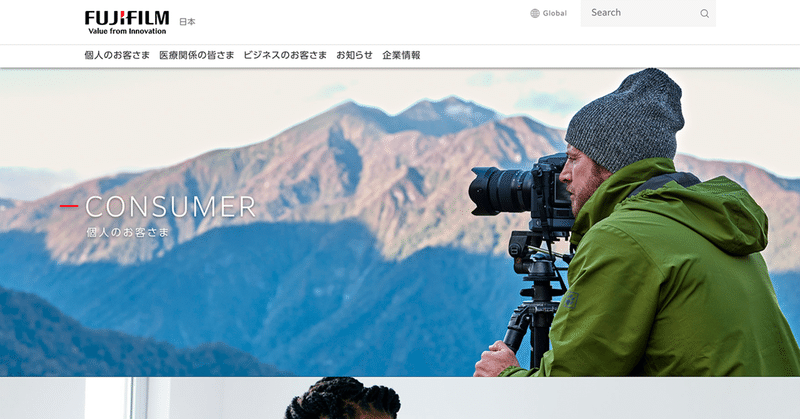
【インタビュー】わたしの“推し”フォント 第8回 桑原 翔(1PAC. INC.)「視覚効果は削ぎ落とせても文字はなくせない。文字の持つ表情がエンドユーザーの印象を決める」
いま、私たちは情報の多くを文字から受け取っています。メディアの中心が印刷物からスクリーンに変わってもなお、文字がコミュニケーションのひとつの要であることは変わりません。
「My MORISAWA PASSPORT わたしの“推し”フォント」では、さまざまなジャンルのデザイン、その第一線で活躍するデザイナーに、文字・フォントをデザインワークのなかでどのように位置づけ、どのような意図・考えで書体を選択しているのかをインタビュー。あわせて、「MORISAWA PASSPORT」“推し”フォントを紹介いただきます。
第8回は、Webサイトを中心にデジタルサイネージ、アプリケーションなどのアートディレクション、フロントエンドのコーディングを手がけるワンパク(1PAC. INC.)の桑原さんにお話を伺いました。
1.デザインがシンプルになることで書体がより重要に
もともとは映像やデジタルアートに興味があったという桑原さん。フォントへの関心が強くなったきっかけは、Webデザインの変遷によるものが大きかったそうです。
「私が最初にWeb表現に興味を持ったのは大学生の頃で、Flash の全盛期でした。Webでこんなことができるのかと思ったのが、この仕事に就くきっかけになっています。
今のWebはパーティクル等の表現やデコレーションが削ぎ落とされ、デザインもシンプルになる傾向ですが、視覚要素が減っても文字は絶対なくなりません。むしろ装飾が少なくなることで、書体が持っている表情がエンドユーザーの印象を決める重要な役割を持つようになったと思います」
Web制作においては、技術の進歩がデザインに変化をもたらします。桑原さんにとって特に大きかったのは、Webフォントの存在でした。
「Webフォントが出始めた頃は、表示速度の問題で部分的にしか使用することができませんでしたが、いまはその心配もありません。すべての文字をWebフォントにすることも可能で、書体を自由に考えることができるようになりました。3G時代と4G時代で提案できるデザインが変わったことを実感しています。
また液晶画面の高精細化が進み、細い文字でもパキッと見えるようになってきました。以前なら見出しには太い文字、というのがセオリーでしたが細い文字を大きく使う、などの表現も今ではよく使われる手法になっています」
また文字情報が多いときには、読みやすさを一番に意識するようにしているそうです。
「装飾性の高いフォントを本文にしてしまうと、読むときにパワーが必要になります。たくさんの文字を読みやすくするにはフォント選びはもちろんですが、文字の配置を数値的に管理して最適な行間や段落間隔を設計するようにしています」
2.作るもののキャラクターに合わせたフォント選び
文字情報の多いWebサイトの場合、読みやすいフォントを選ぶことが最も重要です。スマートフォンや高精細なディスプレイなど、さまざまなデバイスでの見え方も考慮して選ぶ必要があります。
「フォントを選ぶときにはまず、MORISAWA PASSPORTの書体を見ていきます。好きなフォントはもちろんありますが、作ろうとしているデザインのキャラクターに合うかどうかが一番重要です。
コーポレートサイトならブランディングを達成する必要がありますし、法人格としてのキャラクターや世の中に対してのスタンス、世間から認知させたいイメージと合っているかどうかですね」
フォントは「声」のようなものだと語る桑原さん。どの声を選ぶかは、制作チームとクライアントを交えて検討を重ね、決定するのだそう。
「案件がキックオフしてから1~2ヶ月かけてディスカッションします。誰のためのものなのか?どんなブランドイメージなのか?柔らかく見せたいのか、クールな感じを出したいのか?などワークショップを重ねながら、制作とクライアントとが同じ目線に立てるように話し合っていきます。
フォントは書体見本を見て決めるのではなく、実際にメインのコピーをいろんなフォントで試してみてどの声色が一番伝わるかを確認しながら選びます。特に書体レギュレーションが決まっていないサイトリニューアルの仕事の場合、検討するフォントの数もかなり多くなりますね」
MORISAWA PASSPORTを選ぶ理由は、日本語フォントの数が多いこととWebフォントとしてTypeSquareで使えることが挙げられるそうです。
「MORISAWA PASSPORTは、日本語表現をするなら必ず通る道のようなもので、日本語をここまで長く多く使っているメーカーは他にありませんよね。ワンパクではデザインの担当だけでなく、実装担当やディレクターもMORISAWA PASSPORTを入れています。
書体数がものすごく多いし、常に新しい書体が増えていくところがいいです。インストールも簡単なので、新しいフォントもタイムリーにどんどん使っていこうと思えます」
3.桑原さんのデザイン&書体実例
桑原さんの手がける仕事の中でも、特に規模が大きく時間をかけて作られているのがコーポレートサイトです。富士フイルムのコーポレートサイトのトップページはBtoB、BtoCを統合したハブのようなものになっているのだそう。
「富士フイルム様の場合、もともとコーポレート書体として使用されていた新ゴの印象値を維持しつつ、今の時代に合わせてUD新ゴの細めのウエイトをセレクトしました。欧文部分は多言語に対応できるClarimo UDです。文字が多いページでも読み込みが速く、アクセスした瞬間にWebフォントに切り替わる速度感がアピールポイントです」
「スマートフォンサイトではUD新ゴ コンデンス90を使っています。PCサイトの新ゴのイメージと統一させつつ、スマートフォンの狭い横幅でも文字数を入れることができるよう考えました」
デザイン部分を担当したタブレット用アプリの例も見せていただきました。フォント選びはもちろん、視覚的な効果やピクトグラムなど子供が飽きずに学習を進められる工夫が詰まっています。
「ベネッセコーポレーション様「チャレンジタッチ」のUIでは、醸成すべき印象値がまったく違うので発想を変えてデザインしています。
小学生向けの教材であるため、使用するのは学校で習う字形を正しく表現した学参書体です。見出しなどで遊び心のあるフォントを取り入れ、メリハリが出るよう工夫しました。
子供はわからない部分があると使わなくなってしまいます。迷わずに進められるようピクトグラムの使い方にも定義づけをしています」
4.MORISAWA PASSPORT “推し” フォント
最後に桑原さんがいま、イチオシのMORISAWA PASSPORT“推し”フォントを3つ紹介しましょう。
1. UD新ゴ コンデンス90
「新ゴの表情を残しつつ、フトコロの広さが軽減されています。横幅の限られたスマートフォンの画面でも、より多くの文字を掲載することができます。PCではUD 新ゴ、モバイルではUD新ゴ コンデンスとデザインのイメージを統一しながら使い分けることができます」
2. Clarimo UD PE
「100言語近く対応しているので、グローバル展開の必要なデザインのテンプレートとして使っています。モダンで読みやすいシンプルなデザイン。ウェイトも幅広く揃っていて、日本語書体との混植でも見栄えがよいので重宝しています」
3.中ゴシックBBB
「使い慣れていることもあって、つい使ってしまうフォントです。一見シンプルなゴシック体ですが、拡大するとエッジやハライなどにニュルっとした曲線の色気があるんですよね。そのニュアンスが、柔らかい言葉を伝えるときに合っているように感じます」
制作物の目的やクライアントによって、異なるキャラクターを憑依させるようにしてフォントを選ぶという桑原さん。TypeSquareによるWebフォントの活用やより読みやすい組み方の追求など、質の高いWebデザインにとって文字が占めるウェイトは非常に大きなものだと改めて実感させられました。